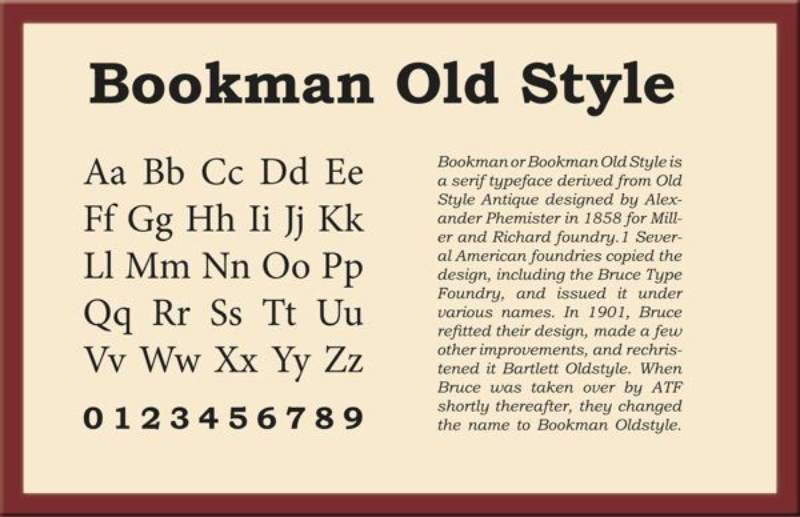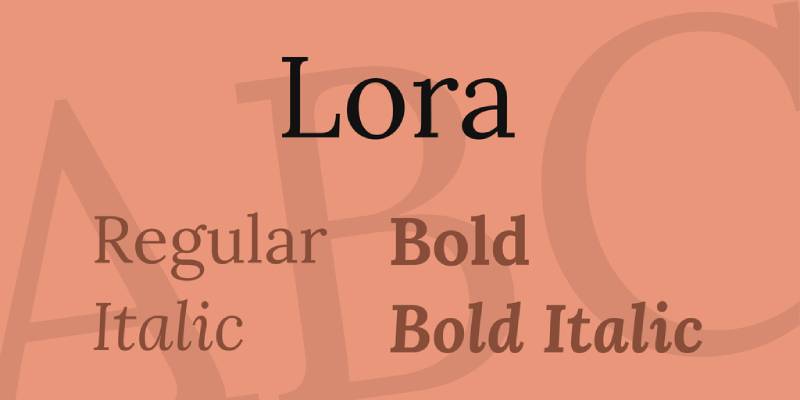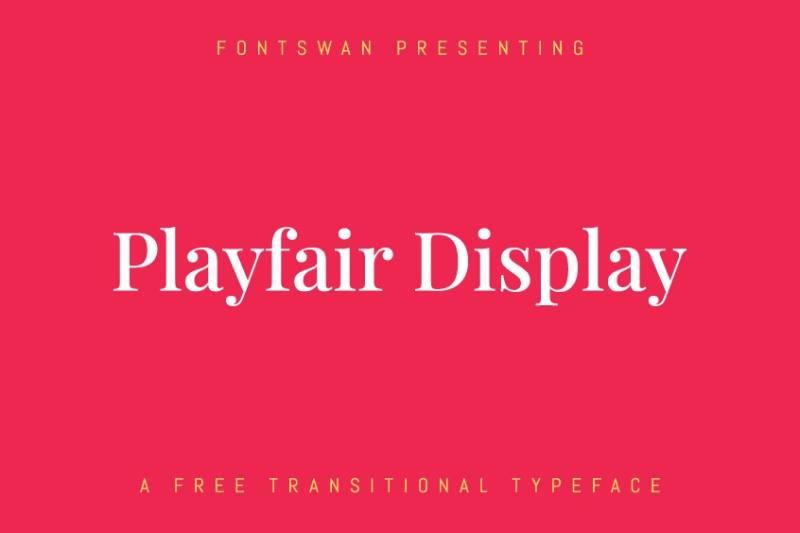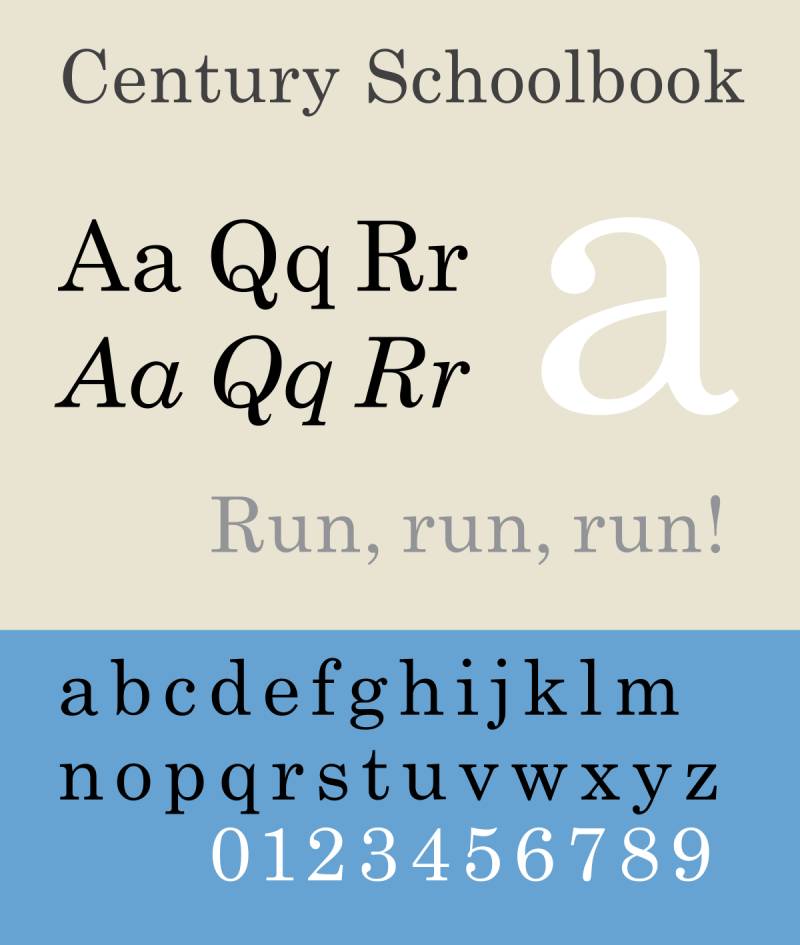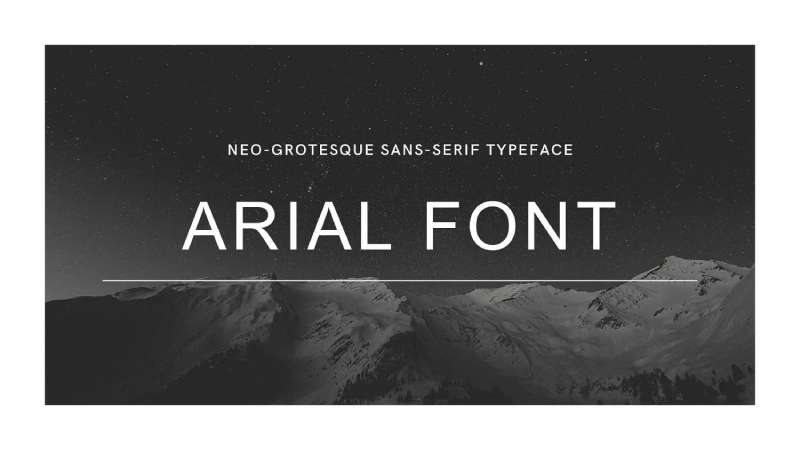
Stellen Sie sich vor: Sie haben einen makellosen Vorschlag ausgearbeitet, Ihre Argumente sind wasserdicht, die Daten sind solide wie ein Fels. Doch dann sagt jemand: „Ich kann das kaum durchstehen bei dieser Schriftwahl.“ Das Herz sinkt.
Schriften, sie sind stille Überzeugungskünstler; unbesungene Helden der Lesbarkeit, des Professionalismus und der Wirkung. Und dennoch werden sie von vielen als nachträglicher Gedanke behandelt. Das ändert sich jetzt.
Die Auswahl der besten Schriften für professionelle Dokumente dreht sich nicht nur um Ästhetik; es geht darum, die richtige Botschaft zu senden, Klarheit zu gewährleisten und die Markenidentität in jeder Zeile, die Sie tippen, zu wahren.
In diesem Raum werden wir die Bedeutung der Schriftkombination, des Zeilenabstands und der Typografie erkunden, Schlüsselelemente, die aus einem langweiligen Dokument ein herausragendes machen.
Am Ende unserer gemeinsamen Reise werden Sie über ein robustes Arsenal an Schriftarten wie Times New Roman und Arial verfügen, ausbalanciert mit gestalterischem Fingerspitzengefühl.
Wir wählen nicht nur Schriften; wir bereiten die Bühne dafür, dass Ihre Worte mit höchstem Professionalismus widerhallen.
Stärke liegt in den Feinheiten – tauchen wir ein in die Welt der Serifen, serifenlosen Schriften und des gestalterischen Feinschliffs in der Dokumentenformatierung.
Die besten Schriften für professionelle Dokumente
| Beste Schriften für professionelle Dokumente | Kategorie/Stil | Design-Ära/Designer | Lesbarkeit | Verwendungskontext |
|---|---|---|---|---|
| Times New Roman | Serif | 1931, Stanley Morison | Sehr hoch | Berichte, Artikel, Lebensläufe |
| Garamond | Altstyle-Serif | 16. Jahrhundert, Claude Garamond | Hoch | Bücher, Zeitschriften |
| Cambria | Serif | 2004, Microsoft ClearType | Hoch | Web, elektronische Dokumente |
| Georgia | Serif | 1993, Matthew Carter | Sehr hoch | Web, Druck |
| Baskerville | Übergangs-Serif | Mitte des 18. Jahrhunderts, John Baskerville | Hoch | Bücher, wissenschaftliche Arbeiten |
| Merriweather | Serif | 2011, Sorkin Type Co. | Hoch | Lesbarkeit im Web |
| Bookman Old Style | Serif | Ende des 19. Jahrhunderts | Hoch | Überschriften, Druckmaterialien |
| Lora | Serif | 2011, Cyreal | Hoch | Digitale und gedruckte Medien |
| Playfair Display | Serif | 2011, Claus Eggers Sørensen | Moderat-Hoch | Titel, elegante Materialien |
| Century Schoolbook | Serif | Anfang des 20. Jahrhunderts | Hoch | Lehrbücher, juristische Dokumente |
| Arial | Serifenlos | 1982, Robin Nicholas und Patricia Saunders | Sehr hoch | Berichte, Präsentationen |
| Helvetica | Serifenlos | 1957, Max Miedinger | Sehr hoch | Beschriftung, Textkörper |
| Verdana | Serifenlos | 1996, Matthew Carter | Sehr hoch | Web, kleine Textlesbarkeit |
| Calibri | Serifenlos | 2007, Lucas de Groot | Hoch | Bürodokumente |
| Roboto | Serifenlos | 2011, Google | Hoch | Digital, mobil und Web |
| Proxima Nova | Serifenlos | 2005, Mark Simonson | Hoch | Digital und Druck |
| Futura | Geometrische Serifenlos | 1927, Paul Renner | Moderat | Anzeigen, Logos |
| Open Sans | Serifenlos | 2011, Steve Matteson | Hoch | Web, Druck |
| Gill Sans | Humanistische Serifenlos | 1928, Eric Gill | Hoch | Beschilderung, Werbeanzeigen |
| Frutiger | Humanistische Serifenlos | 1976, Adrian Frutiger | Hoch | Beschilderung, Unternehmensidentität |
Top Serifenschriften
Times New Roman
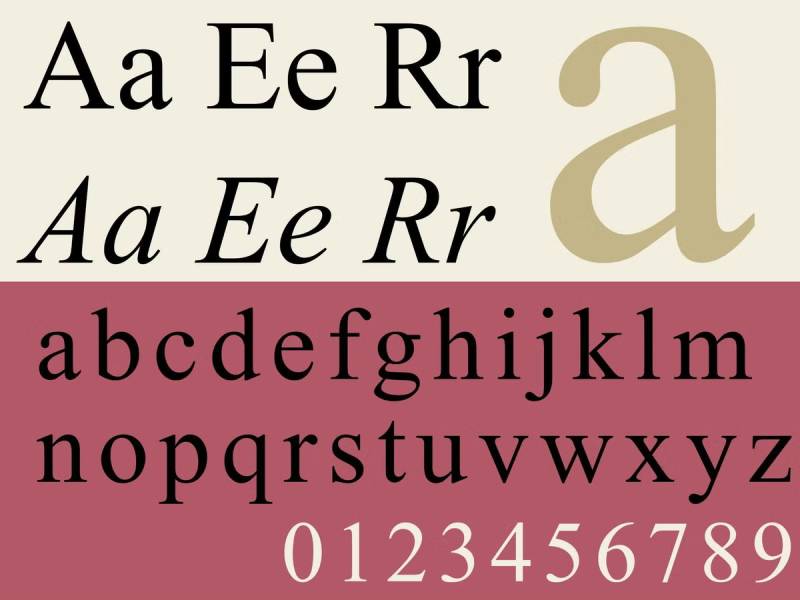
Sie kennen sie. Sie haben sie verwendet. Times New Roman ist die quintessentielle professionelle Schrift. Es ist wie dieser zuverlässige Freund, der immer für Sie da ist. Perfekt für alles von Berichten bis hin zu Lebensläufen. Sie hat diesen altmodischen Charme, aber auf gute Weise, wissen Sie?
Garamond
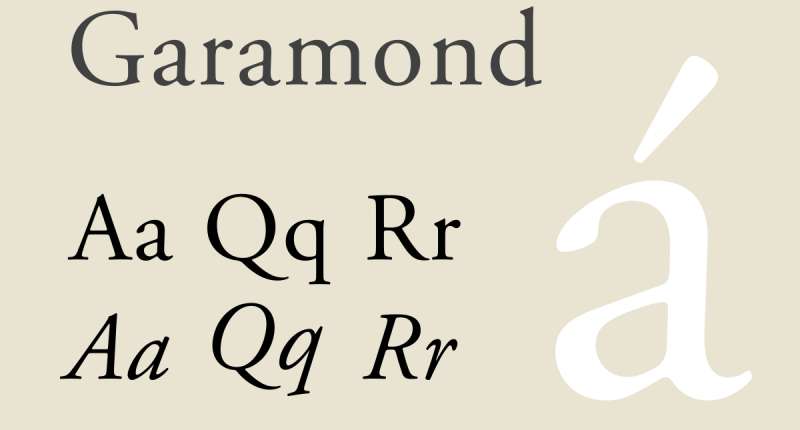
Als nächstes Garamond. Diese Schrift hat Stil und Eleganz. Sie ist eine dieser Schriften, die sagen: „Ich meine es ernst, aber ich habe auch Stil.“ Großartig, wenn Ihr Dokument einen Hauch von Raffinesse benötigt.
Cambria
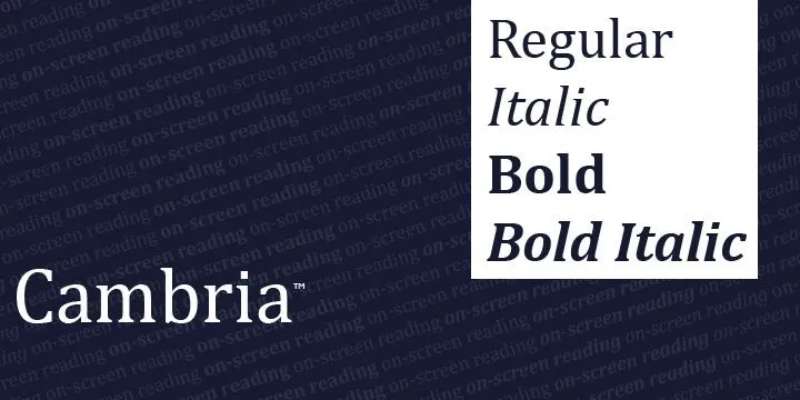
Cambria. Oh, diese ist ein Juwel für das Lesen am Bildschirm. Sie ist wie die jüngere, coolere Schwester von Times New Roman. Entwickelt für Klarheit, insbesondere auf Bildschirmen, ist sie eine solide Wahl für E-Dokumente.
Georgia
Georgia – eine moderne Serifenschrift. Sie ist wie das freundliche Gesicht in einer Menschenmenge. Entworfen für den Bildschirm, ist sie super lesbar, auch bei kleineren Größen. Wenn Ihr Dokument auf Bildschirmen gelesen wird, ist Georgia Ihre erste Wahl.
Baskerville
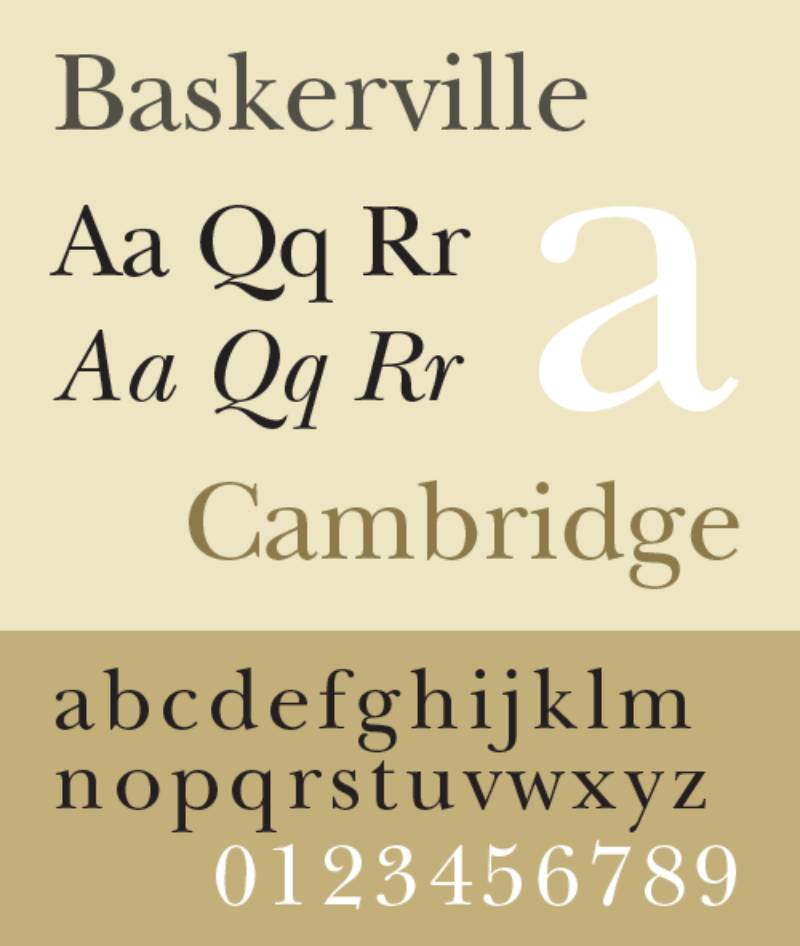
Baskerville. Diese Schrift ist klassisch, mit einem Hauch von Luxus. Es ist so, als würde man eine Designeruhr tragen. Sie ist nicht laut, aber sie spricht von Qualität und Raffinesse.
Merriweather
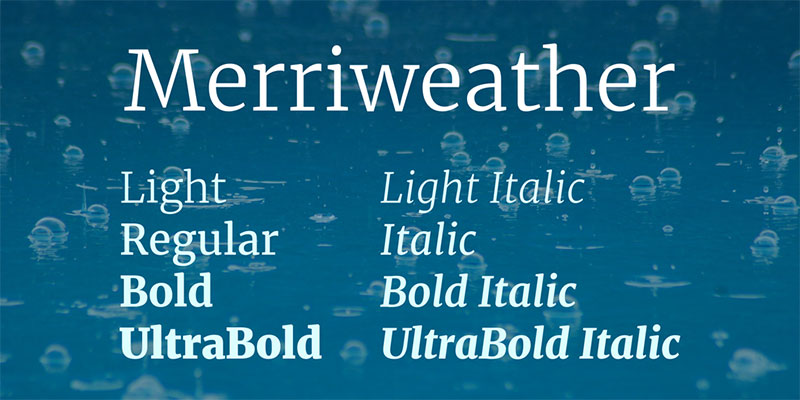
Für Webinhalte ist Merriweather ein Star. Es ist eine neuere Schrift, hat aber schnell ihren Platz verdient. Sie ist angenehm für die Augen, was perfekt für längere Lesezeiten auf Bildschirmen ist.